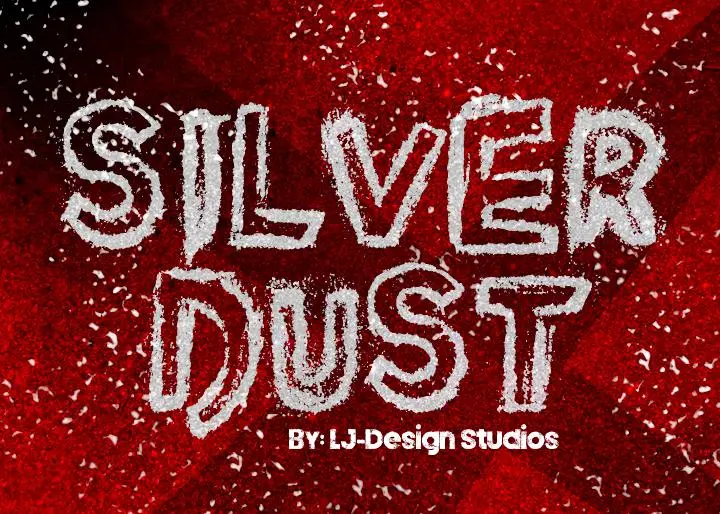
Silver Dust font – Download Grátis
A fonte Silver Dust é uma escolha perfeita para projetos que buscam expressar personalidade e sofisticação. Se você está procurando por uma fonte script elegante, essa opção é certamente para você. Com suas linhas suaves e harmoniosas, a Silver Dust oferece um toque pessoal e específico em qualquer projeto onde desejará transmitir uma mensagem mais íntima ou delicada. Esta font foi criada pelo designer Hamilton, que incorporou elementos de sua visão única no design para criar algo verdadeiramente único. Suave mas poderosa, a Silver Dust é perfeita para se destacar em um layout onde você deseja comunicar seu estilo com mais profundidade e autenticidade. Com uma variedade de tamanhos e estilos, a fonte Silver Dust é ideal tanto para uso pessoal quanto para projetos que requerem personalização. Eles não são apenas fáceis de ler em pequenos detalhes ou grandes textos, mas também fornecem um tom adequado para qualquer tipo de aplicação gráfica onde você deseja transmitir seu estilo. Se você está procurando por uma fonte que dê uma sensação de personalidade e sofisticação ao mesmo tempo, Silver Dust provavelmente é a escolha certa. Essa elegante font script do designer Hamilton criada para uso pessoal, mas também adequado para um amplo espectro de projetos gráficos.